À l'église de Calviac-en-Périgord 24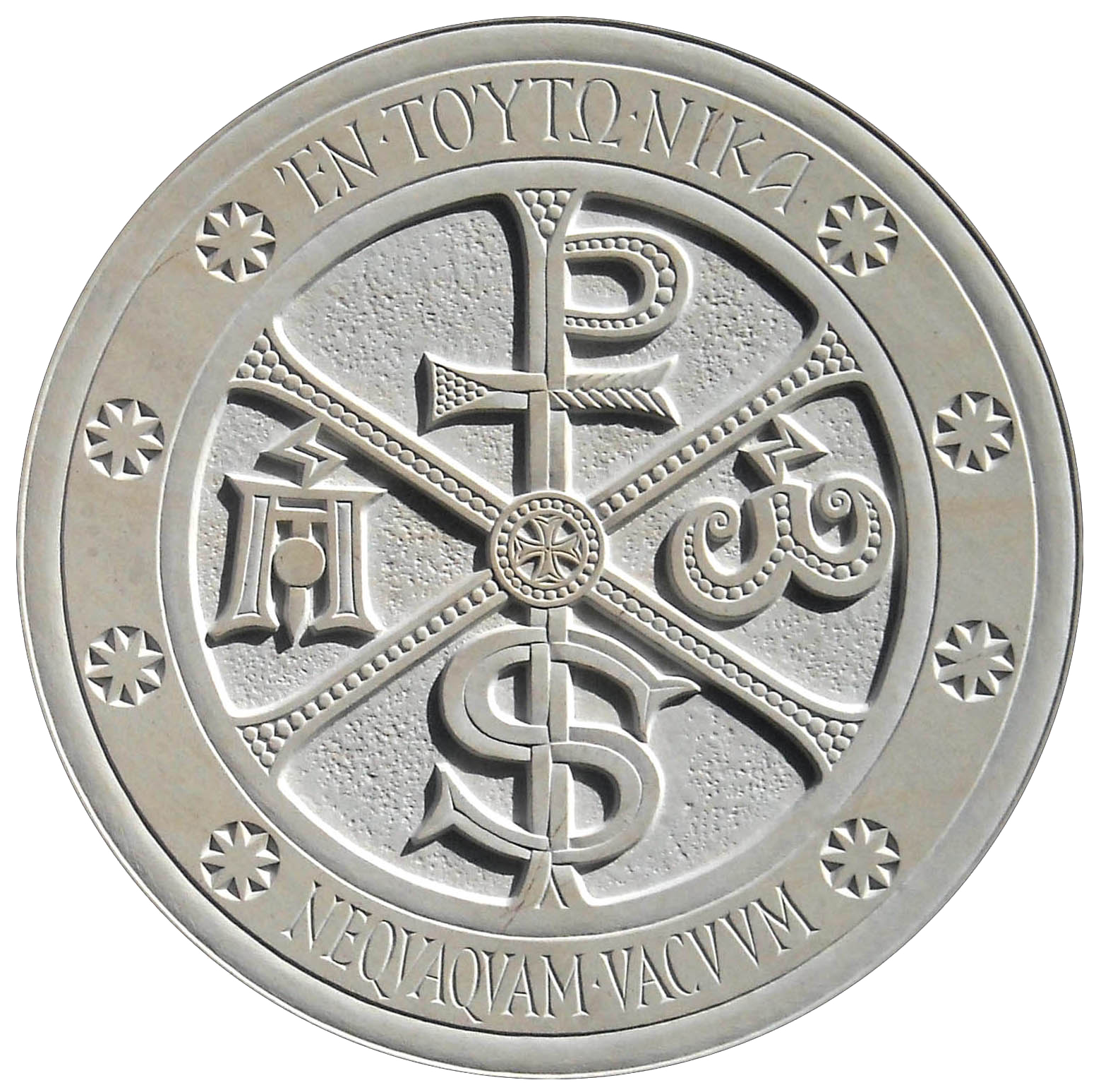
Chrisme (face cachée du cube Métatron ?). On ne peut pa définir ce qui se passe dans cet État, pour comprendre cet État il faut passer par Lui.
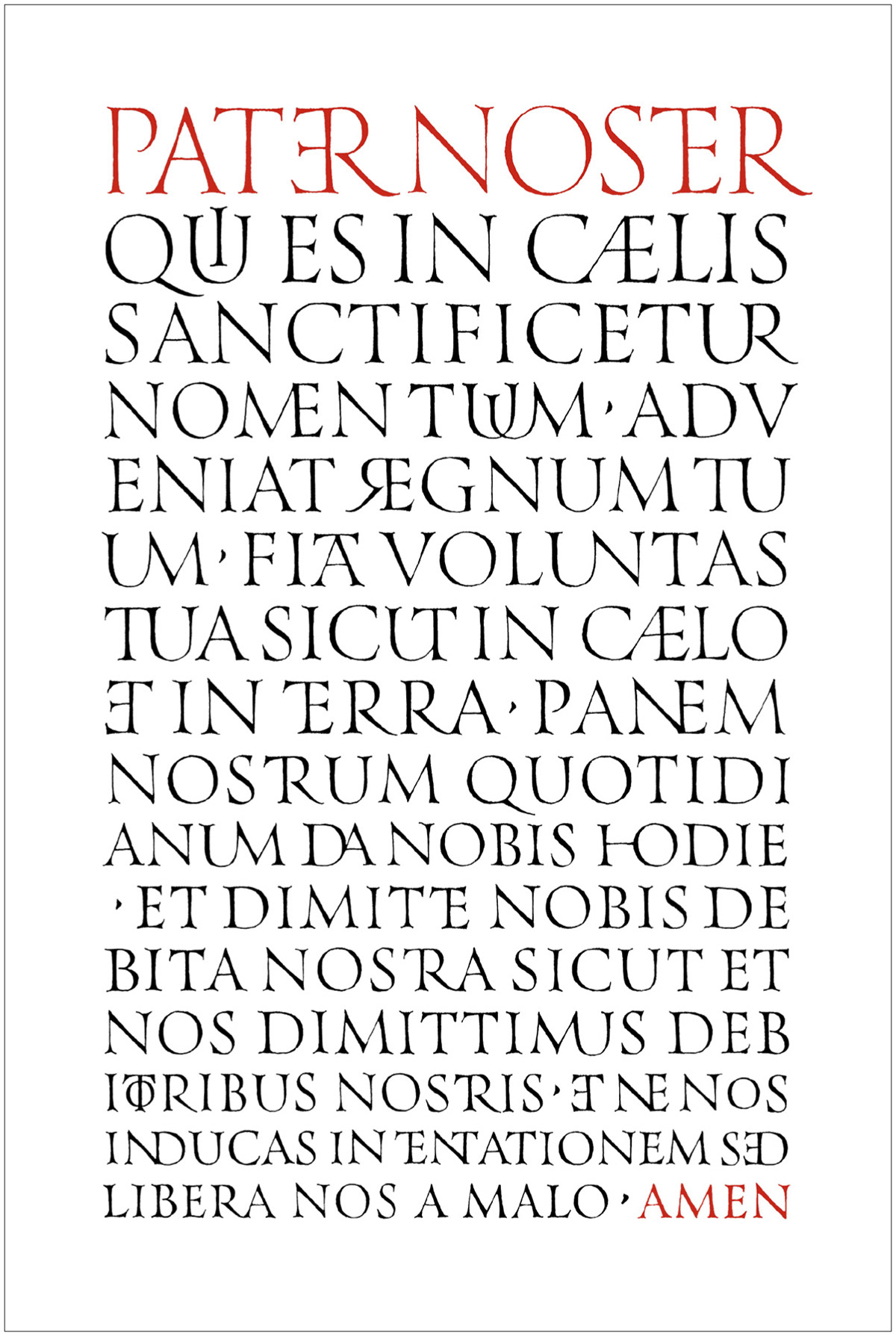Recherche de composition
AUM en sanskrit (amen, amin...)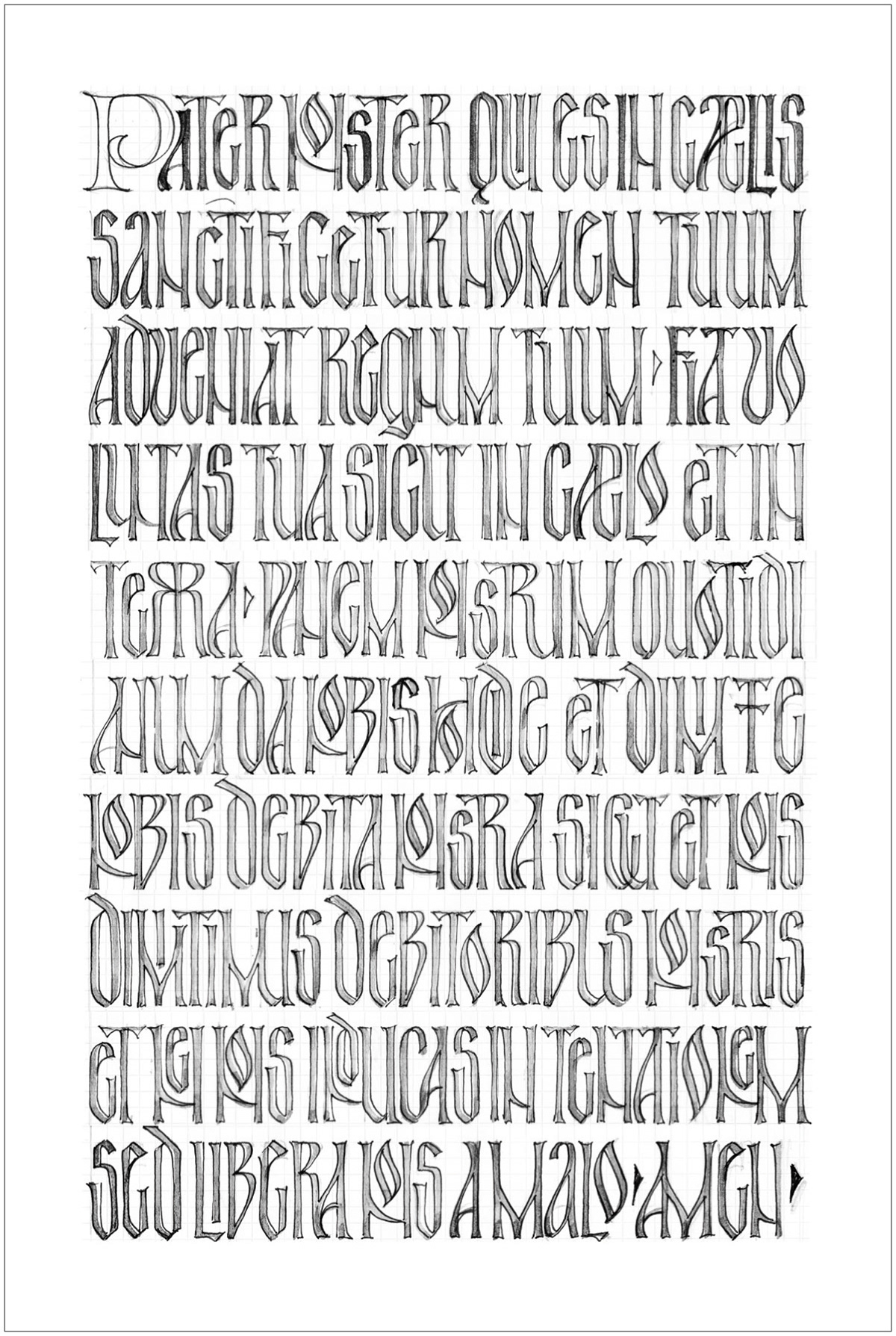
Croquis - Pater Noster avec effet cyrillique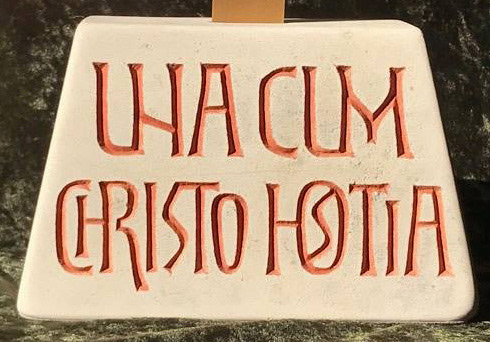
Socle pour un Christ
Croquis pour chemin de croix
Vertus théologales
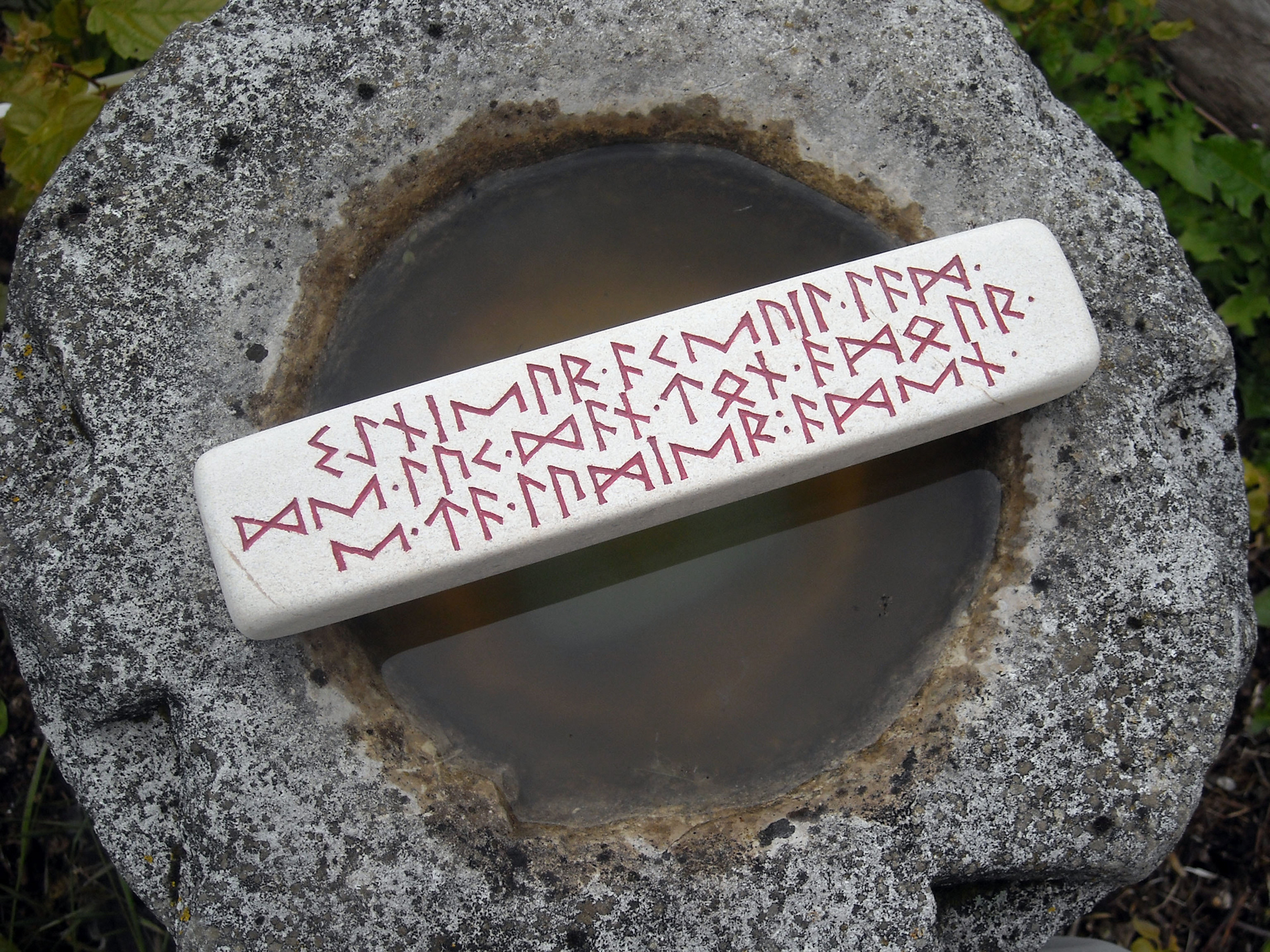Vertus théologales
Runes celtiques
Prière cathare en Occitan
Ichtus
Chrisme
Pierre harmonique pour mini-champ morphogénétique.
Graine de vie
Arbre séphirotique
Alpha et Oméga, et lemniscate
Triskell